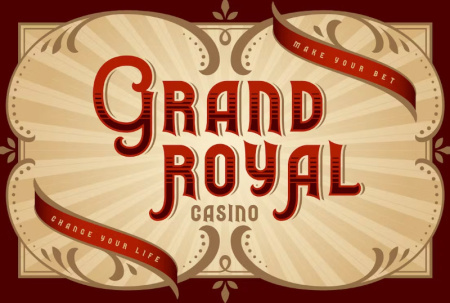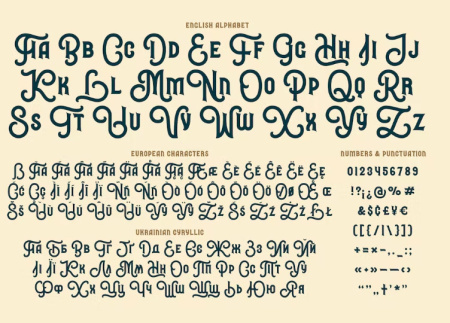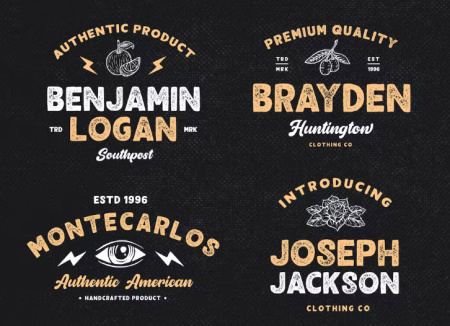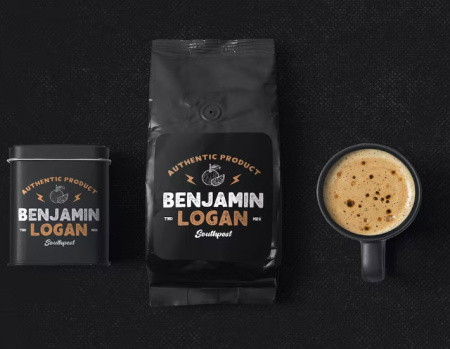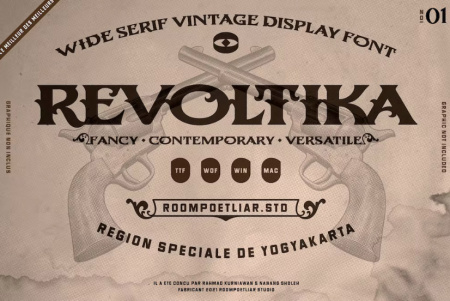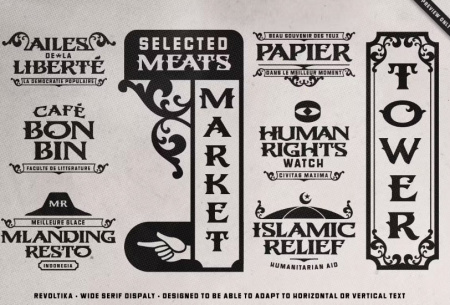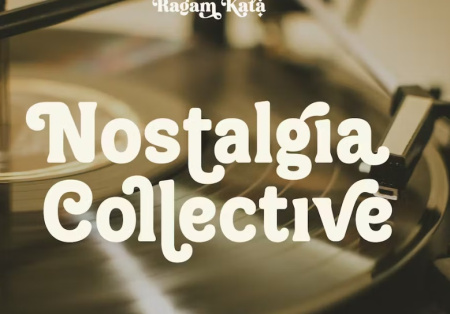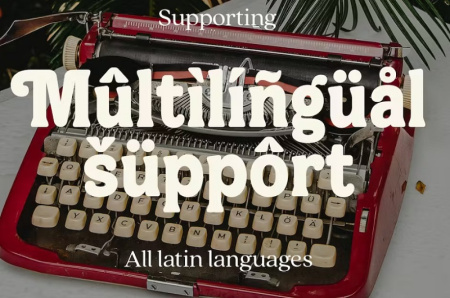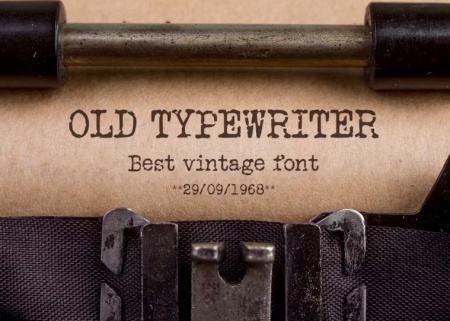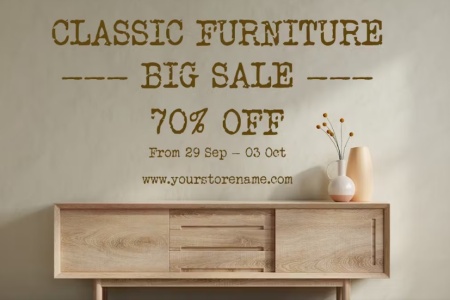
فونت انگلیسی طرح قدیمی vintage font
1- دانلود فونت های انگلیسی طرح قدیمی و کلاسیک vintage font
در این پست با معرفی مجموعه فونت های قدیمی فونت انگلیسی و کلاسیک با شما همراه هستیم. دانلود فونت انگلیسی طرح قدیمی vintage font با ظاهری قدیمی و کلاسیک غربی می باشد. این مجموعه شامل فونت هایی است که می توانید از آن برای ایجاد یک لوگوی قدیمی برای برندسازی، طراحی تایپوگرافی، جلد مجله یا کتاب، سربرگ وب سایت، بسته بندی محصول، طراحی تی شرت، پوستر برچسب و بسیاری موارد دیگر استفاده کنید.
همچنین این یک فونت های انگلیسی قدیمی برای پروژه های برندسازی، آرم ها، طرح های عروسی، پست های رسانه های اجتماعی، تبلیغات، بسته بندی محصولات، طرح های محصول، برچسب، عکاسی، واترمارک، دعوت نامه، لوازم التحریر، رویدادهای مذهبی، تابلوهای علامت گذاری و هر پروژه ای مناسب است.
2- فونت انگلیسی به سبک قدیمی
با این فونت انگلیسی به سبک قدیمی می توانید عناوین شگفت انگیزی را برای جلد کتاب، جلد سی دی، پوستر، لوگو، تبلیغات، پست و استوری و ... ایجاد کنید. فونت انگلیسی قدیمی Nostalgia Collective شامل فایل های TTF,OTF,WOFF می باشد.
3- فونت انگلیسی ماشین تایپ قدیمی
فونت Old Typewriter یک فونت انگلیسی ماشین تایپ قدیمی زیبا است که یادآور سبک کلاسیک و قدیمی است. می توانید از این فونت برای روزنامه‌ها، تیترها، پوسترها، مجلات، چاپ تی‌شرت، هنرهای دیواری و موارد دیگر استفاده کنید.
4- دانلود فونت انگلیسی قدیمی برای فتوشاپ
Old Linoleum یک فونت قدیمی فوق العاده جالب و ساده است. این فونت با طراحی گچی و قدیمی برای طیف گسترده ای از ایده های خلاقانه مناسب می باشد.
ویژگی های فونت انگلیسی طرح قدیمی vintage font
✅ نام فونت انگلیسی: 1 Revoltika Vintage
✅ نام فونت انگلیسی 2 : Rodetta - Vintage Font
✅ نام فونت انگلیسی 3 : Fortune Vintage Font
✅ نام فونت انگلیسی 4 : Nostalgia Collective
✅ نام فونت انگلیسی 5 : Old typewriter
✅ نام فونت انگلیسی 6 : Old Linoleum